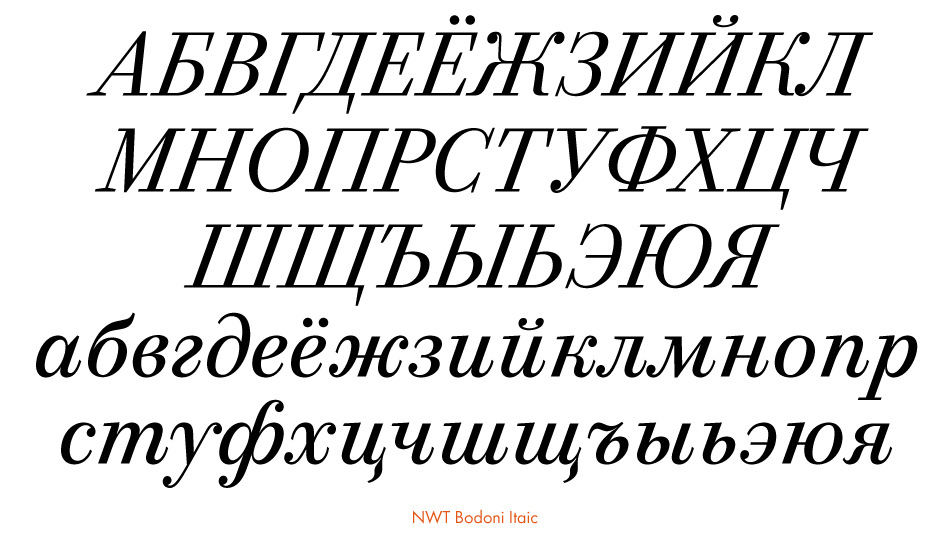
Шрифт прописные буквы русского алфавита: Красивые буквы русского алфавита печатные и прописные для оформления плакатов, стендов, праздников, Дня рождения, Ново…
Не знаете, как оформить красивым шрифтом заголовок или надпись в режиме онлайн? Думаете для этого необходимо уметь пользоваться графическими редакторами на подобие Photoshop, а также иметь здоровую фантазию? А вот и нет. Специально для того, чтобы пользователи смогли написать текст необычным, замысловатым шрифтом существуют онлайн сервисы. Предоставляются большинство из них абсолютно бесплатно, для этого нужно вписать свои строки в специальное поле, и программа предложит вам различные варианты оформления красивой надписи. Самые популярные мы рассмотрим в этой статье.
Online-letters.ru – один из самых популярных сайтов с онлайн шрифтами в Рунете. Страница сайта имеет самое необходимое – то, зачем пришел посетитель, а именно красивые шрифты по видам и стилям. Попадая на главную страницу http://online-letters.ru , вы увидите перед собой виды шрифтов. Слева в блоке можно выбрать категории, например – печатный, gothic, сказочный.
Чтобы написать текст онлайн шрифтом выберите один из разделов слева.
Сервис красивых шрифтов — online-letters.ru
- Откроется окно, в котором вам нужно вписать текст, который будет преобразован в выбранный вами шрифт. Подтвердите соответствующей кнопкой.
- На следующей странице вы должны выбрать один из предлагаемых вариантов шрифта. Для этого пролистайте и ознакомьтесь со всеми вариантами, а после того, как определитесь с выбором, установите чекбокс напротив нужного шрифта.
- Справа от шрифта появится синяя кнопка «Далее», нажмите на нее.
- В следующем окне вам нужно выбрать цвет шрифта, размер и обводку букв и после нажать «Сгенерировать».
- Откроется окно, в котором вы увидите готовый вариант вашей фразы и варианты ее получения. Вы можете скопировать ссылку для форума, для скачивания, для вставки в HTML-код. Если вы хотите просто скачать надпись на свой компьютер, выберите «Для скачивания», скопируйте ссылку (для этого выделите ее, нажмите правую кнопку мыши и выберите «Копировать».
- Затем откройте новое окно, вставьте ссылку в адресной строке браузера, нажав CTRL+V и перейдите на нее. В открывшемся окне будет ваша надпись, нажмите правую кнопку мыши и выберите «Сохранить».
Gfto.ru — красивый дизайн текста
Сервис написания красивого текста онлайн – http://gfto.ru . Этот сайт предоставляет дополнительные возможности в виде фона текста, а также масштабирования поля вокруг текста и настройки наклона шрифта. Здесь вы можете выбрать красивый шрифт и украсить его специальными шаблонами, которых здесь также имеется большое количество на любой вкус. Для того, чтобы создать свою необычную надпись, перейдите на главную страницу сайта.
X-lines.ru — сервис предоставляет большое количество шрифтов
Еще один сервис, который предоставляет пользователям создать текст с красивым шрифтом x-lines.ru. Дизайн сайта, как и в первом рассматриваемом сайте, без излишков, только то, что нужно пользователю. В левом блоке сайта находятся категории шрифтов.
Выбрав одну из категорий вам предлагают выбрать стиль шрифта, указывая понравившийся из списка.
Перейдите на главную страницу сайта – http://x-lines.ru и выберите нужную категорию.
Сервис написания красивым шрифтом — x-lines.ru
- Введите текст в нужное поле и нажмите «Далее».
- В следующем окне выберите нужный шрифт и поставьте чекбокс напротив него, после чего нажав «Далее».
- На странице вы увидите палитру цветов, где необходимо указать нужный и выбрать размер текста из списка и нажмите кнопку «Сгенерировать».
- В окне откроется несколько вариантов сохранить красивый шрифт. В блоке «Ссылка на картинку» выделите ссылку и скопируйте для вставки в новое окно, где вы сможете ее сохранить.
Cooltext.com — уникальные шрифты
Онлайн-сервис cooltext.com является англоязычным и русской версии, к сожалению, не имеет. Но есть в этом и положительный момент – он здесь практически не нужен. Ведь все, что нам нужно, это выбрать понравившуюся надпись из богатого списка и красиво написать в окне нужный нам текст.
А если вы пользуетесь браузером Chrome, то вы можете просто в один клик перевести страницу, для других браузеров есть также расширение-переводчики. Сайт приятно отличается от предыдущих тем, что здесь имеются уже готовые варианты как красивых шрифтов, так и их оформления в различных цветах и стилях.
Перейдя по ссылке https://cooltext.com/ на главную странице вашему взору открываются варианты готовых шрифтов, оформленных в виде логотипов. Для выбора других стилей, внизу вы найдете категории под заголовком «Generator categories».
Вводим в поле ввода необходимый текст — Cooltext.com
Fonts-online.ru добавляем текст удобно и быстро
Данный сайт также предназначен для написания вашего текста красивым шрифтом – Fonts-online.ru. Он содержит огромную базу шрифтов различного направления, вида и стиля. Такому набору сайт обязан большинству пользователей, которые могут самостоятельно добавить на сайт новый шрифт. Все здесь имеющиеся шрифты поделены на латинские, кириллические, графические, рукописные, декоративные, граффити и т.
- Если вы решили использовать фломастеры или цветные карандаши, то начните с обрисовки контура букв. Это делается простым карандашом. Контур далее обводится фломастером, и только потом буква закрашивается красками или карандашами.
- Чтобы надпись не выглядела скучно, можно за буквами дорисовать тени. Это создаст иллюзию наличия стены за объемными буквами, которые отбрасывают тень.Буквы, нарисованные в трехмерном виде, также приобретают дополнительный объем.
- определяемся, в каком месте будет располагаться надпись